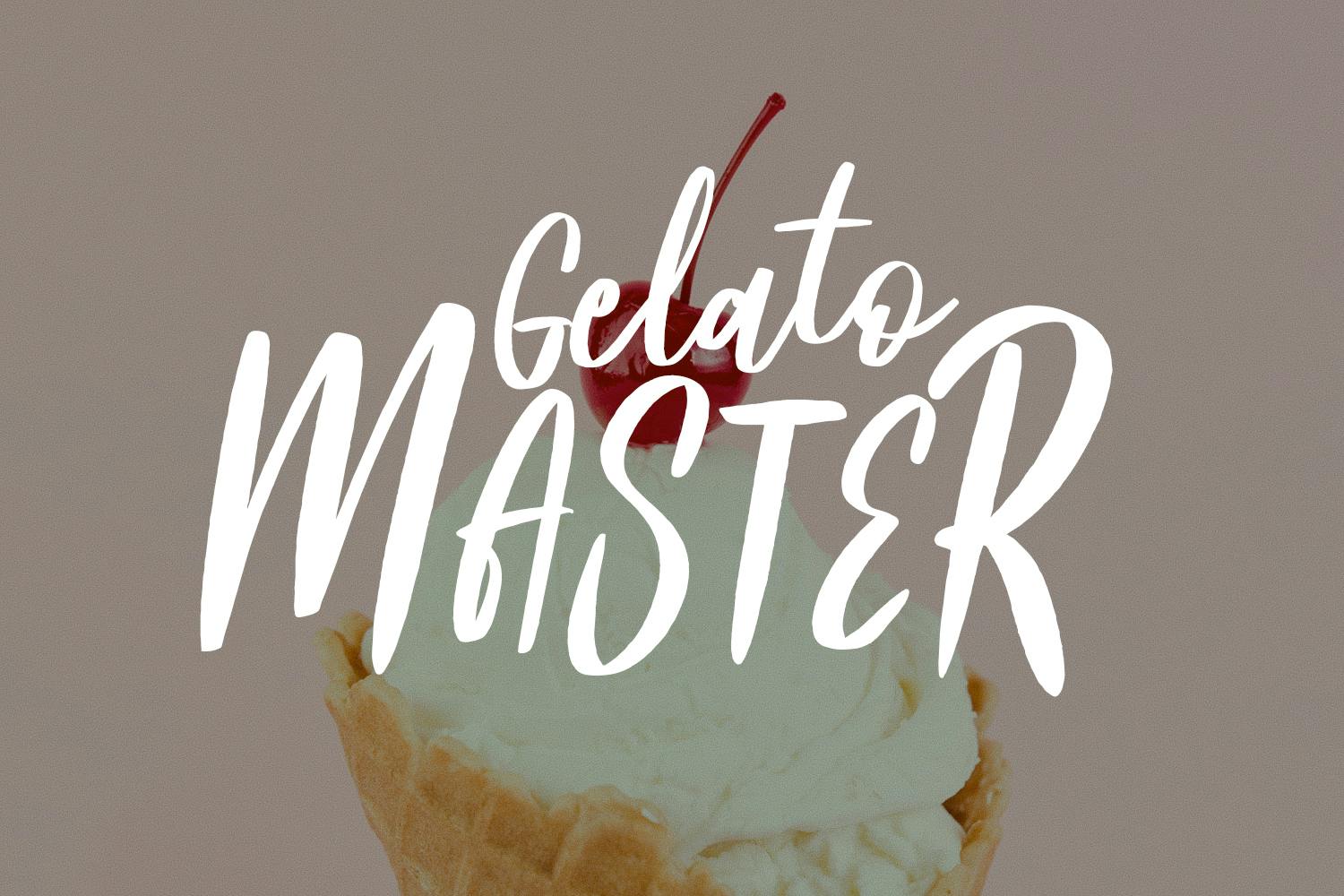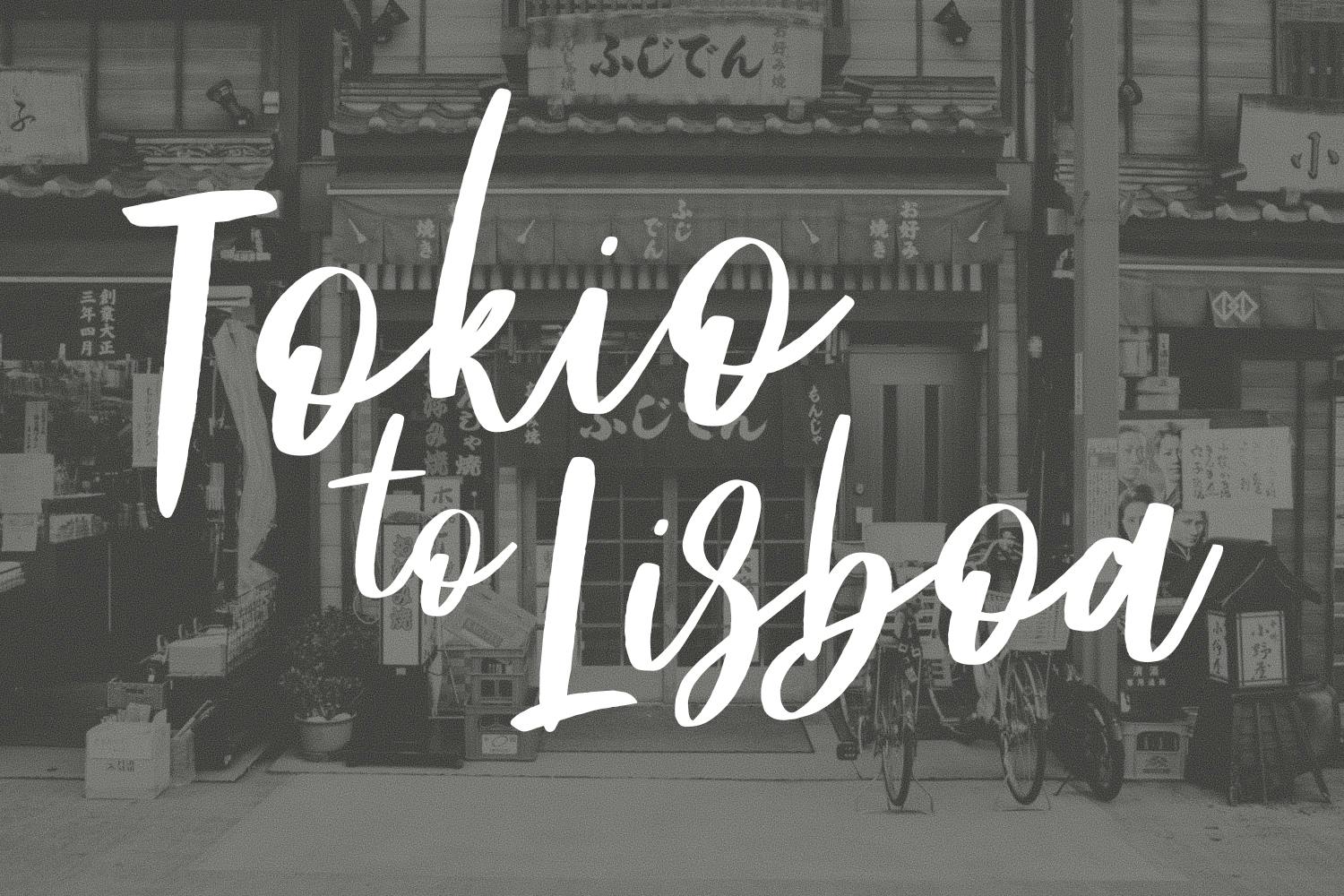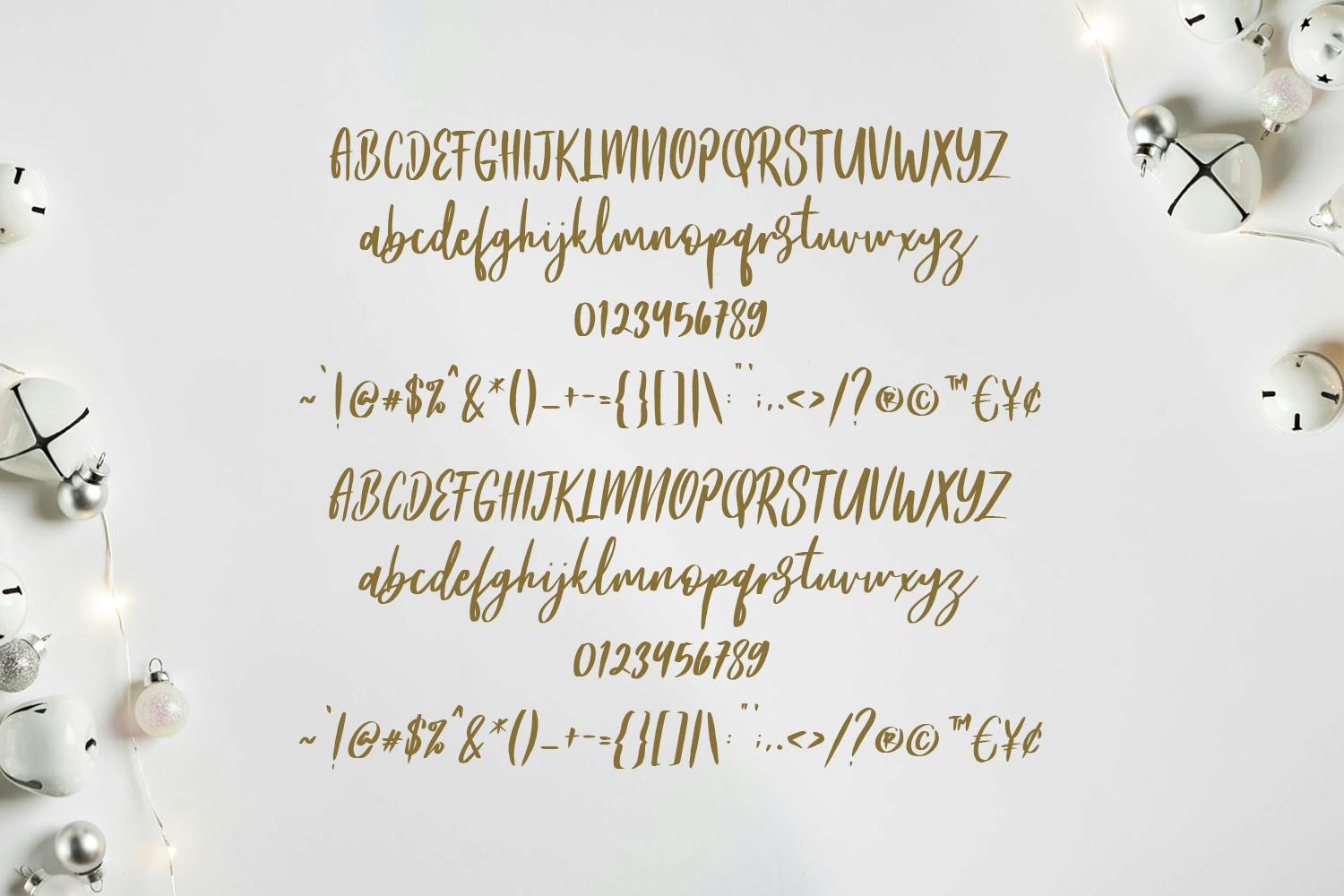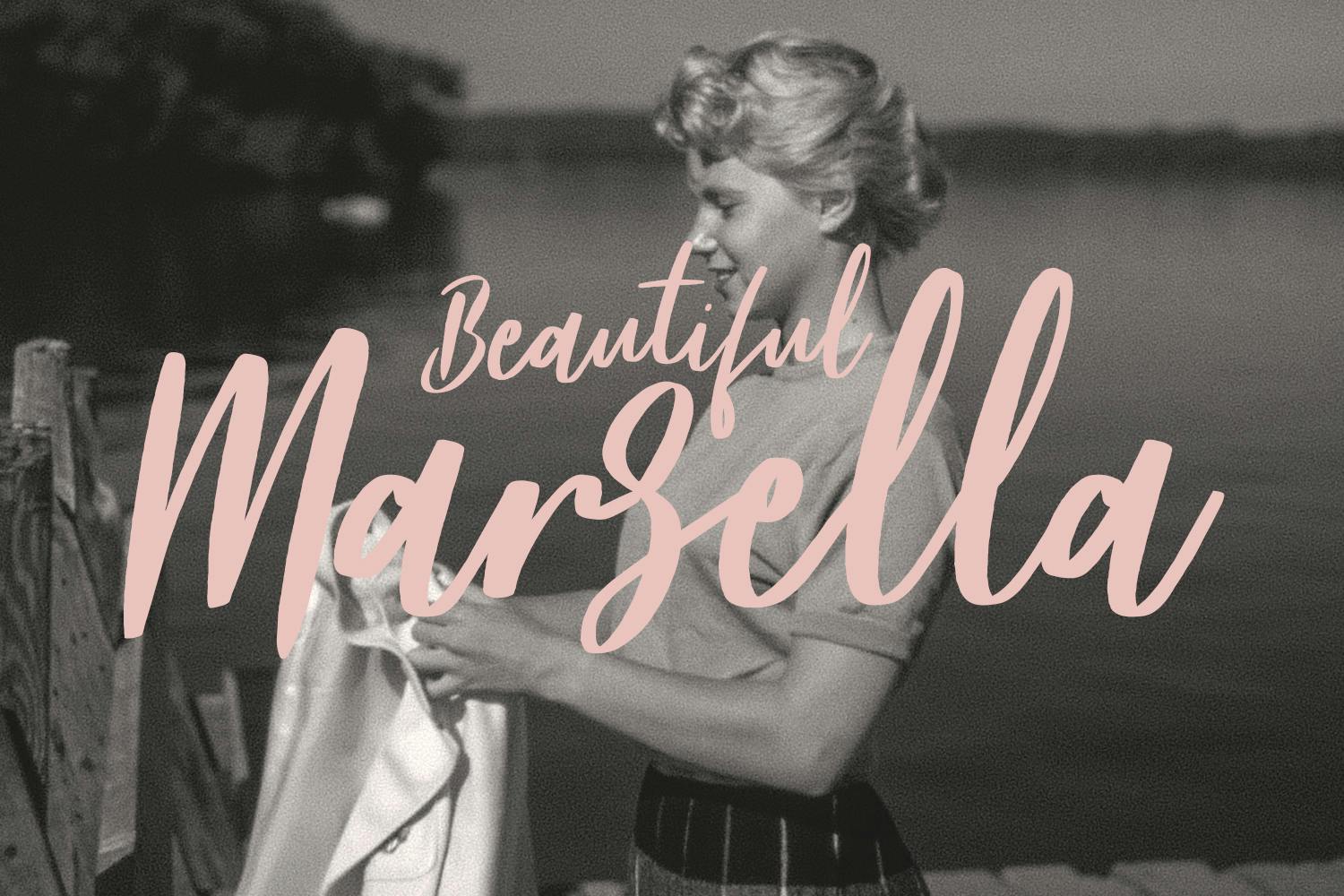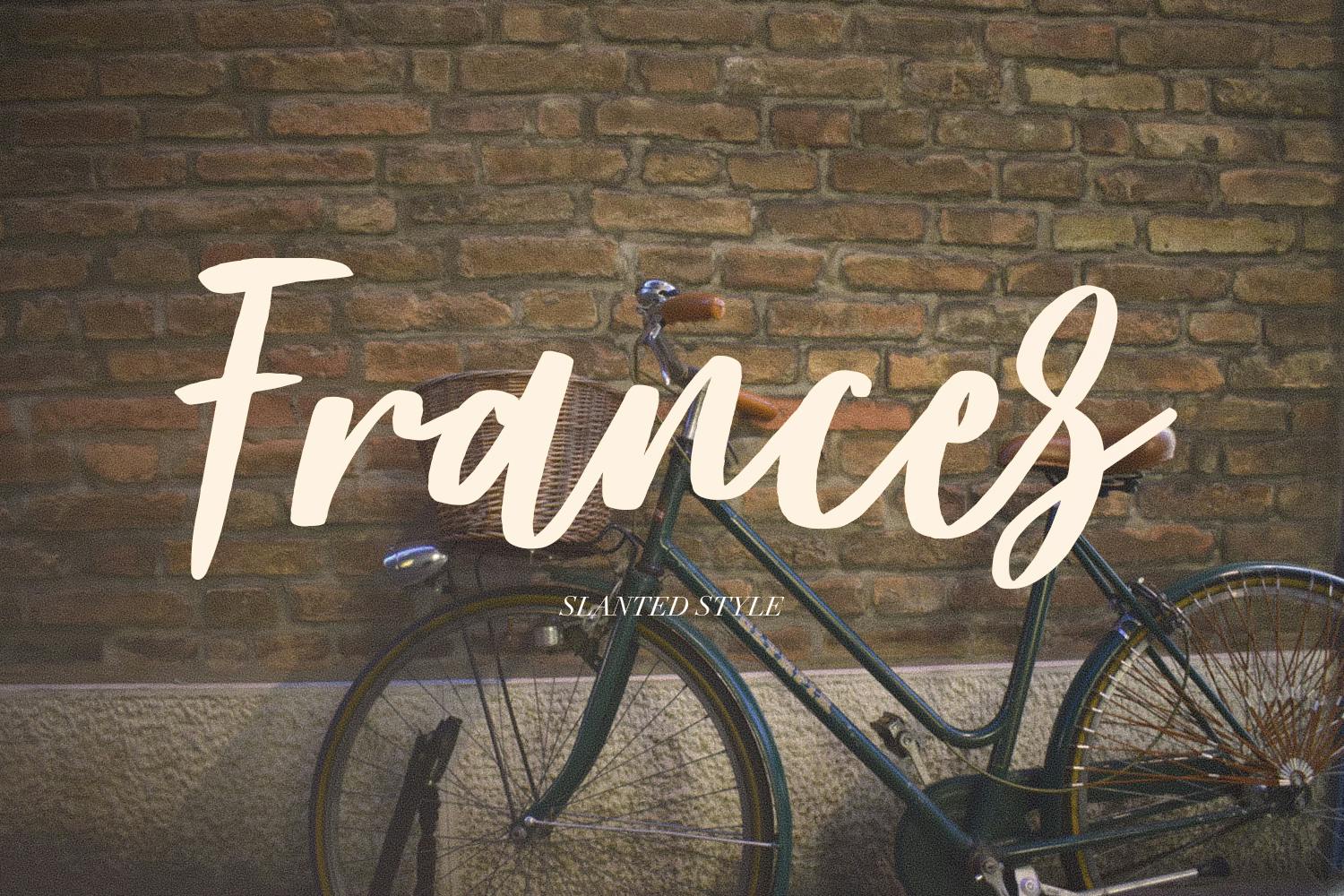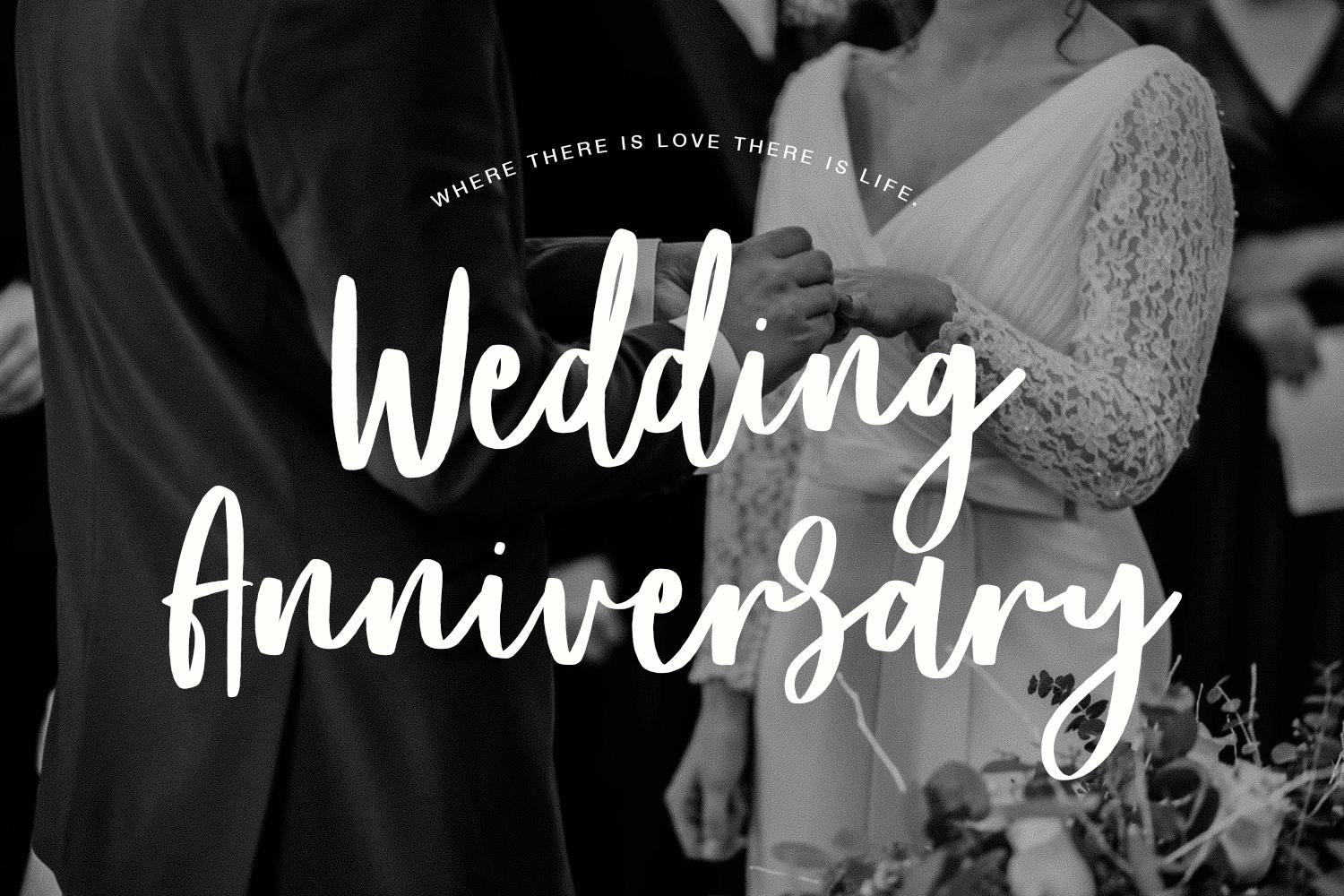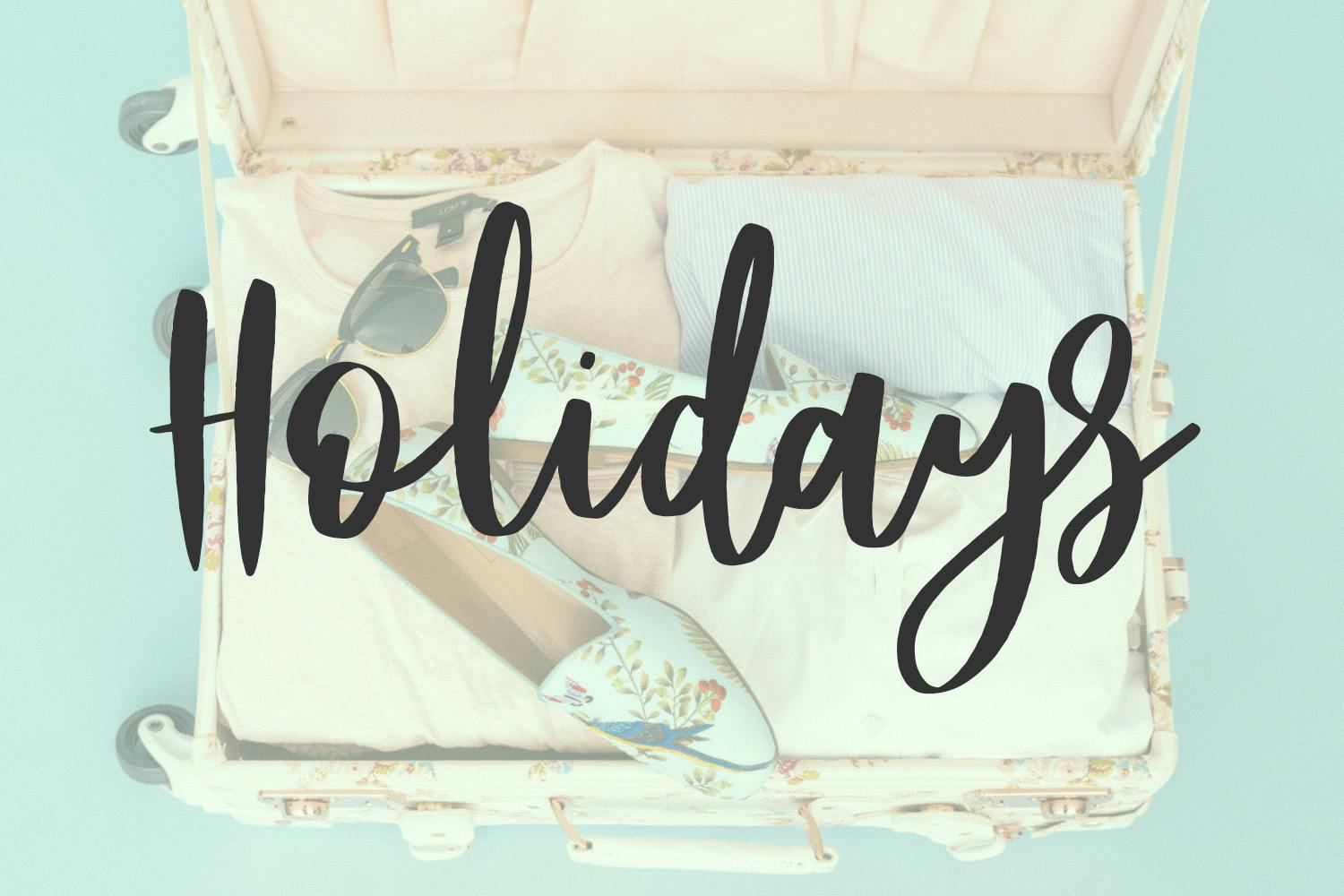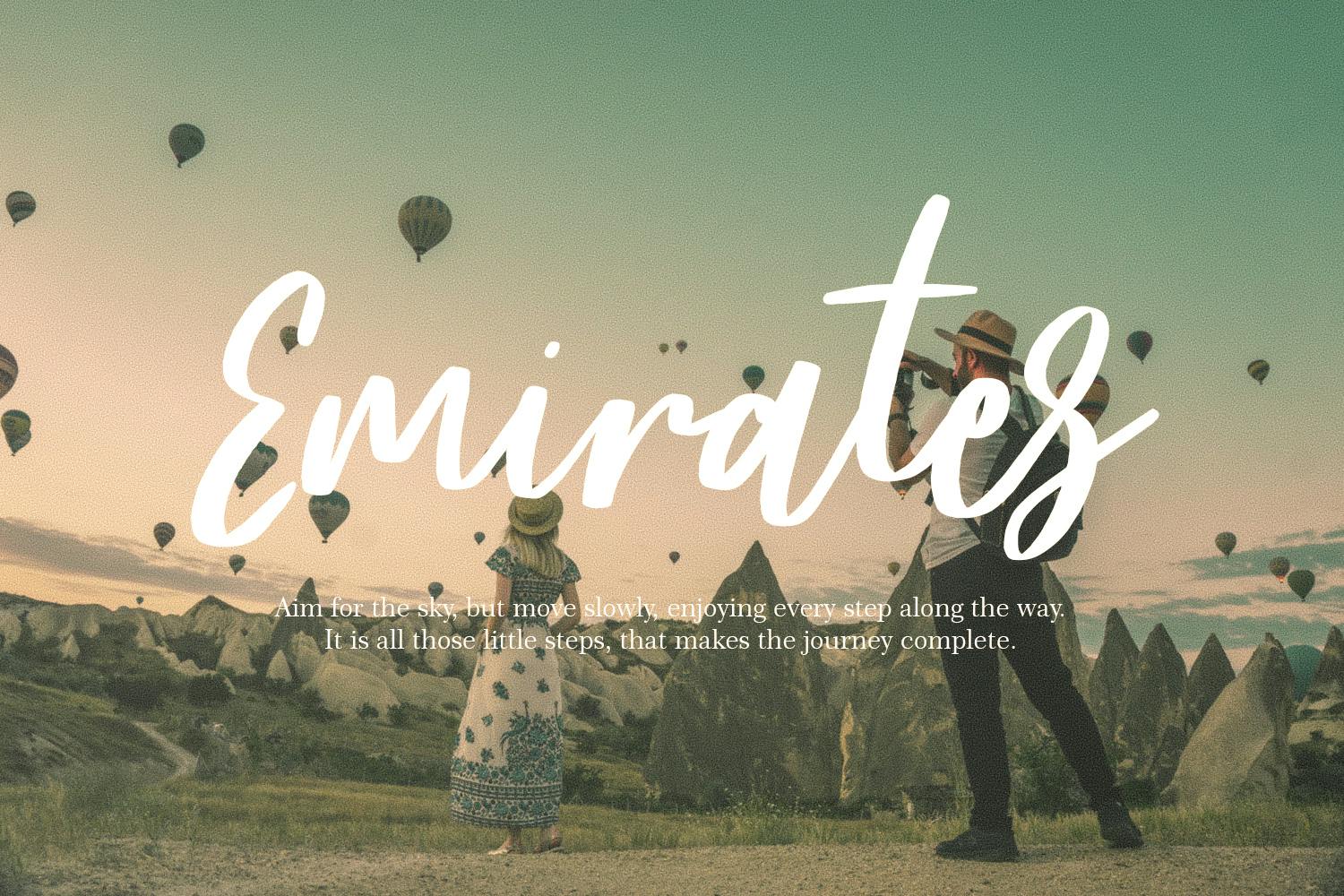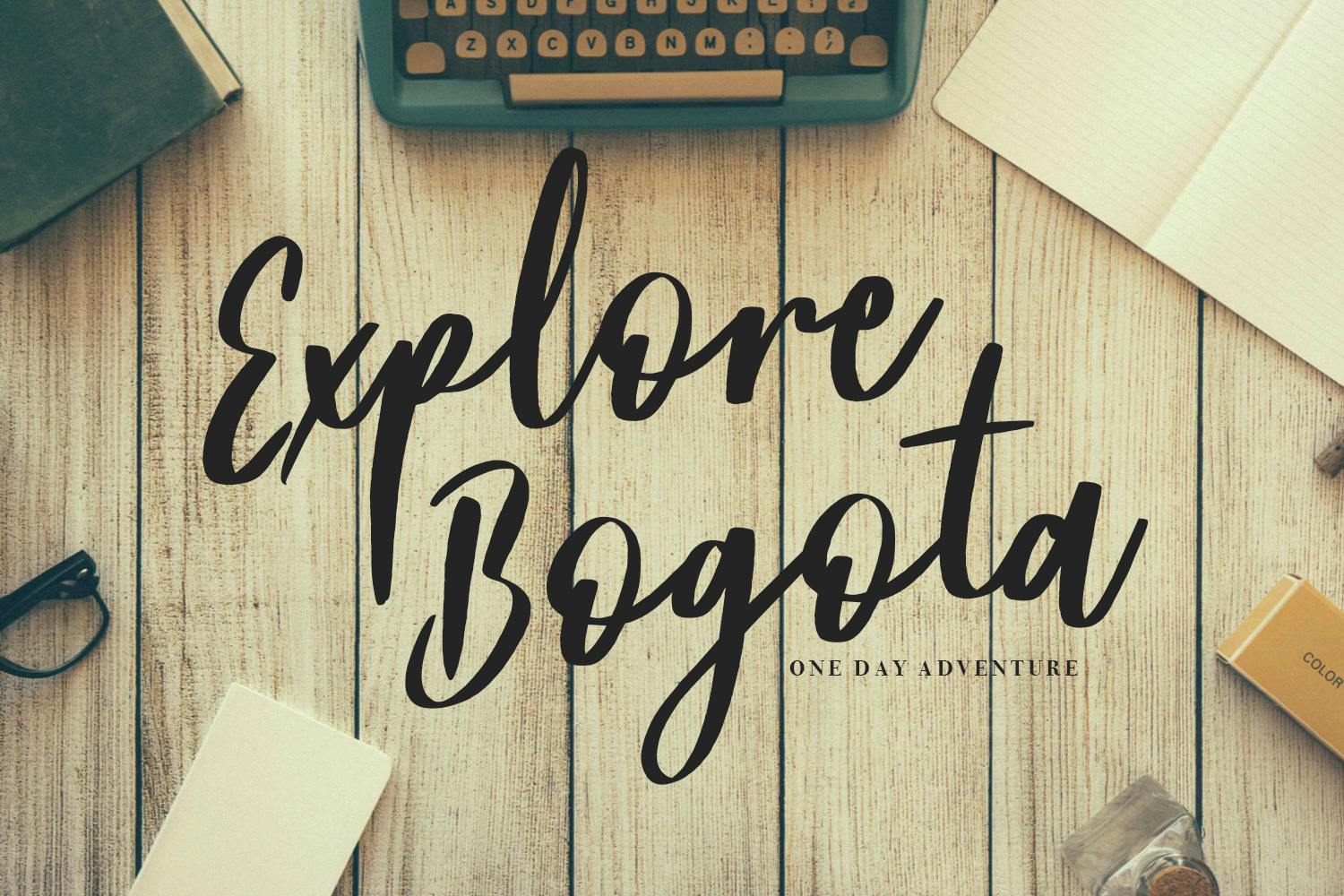
فونت Frances یک انتخاب عالی برای طراحیهای شماست که حس دستساز و اصیل را به ارمغان میآورد. این فونت بهخوبی برای امضاها، لوازمالتحریر، لوگوها، نقلقولهای تایپوگرافی، جلد مجلات یا کتابها، هدر وبسایت، لباس، برندینگ، طراحی بستهبندی و موارد دیگر مناسب است.